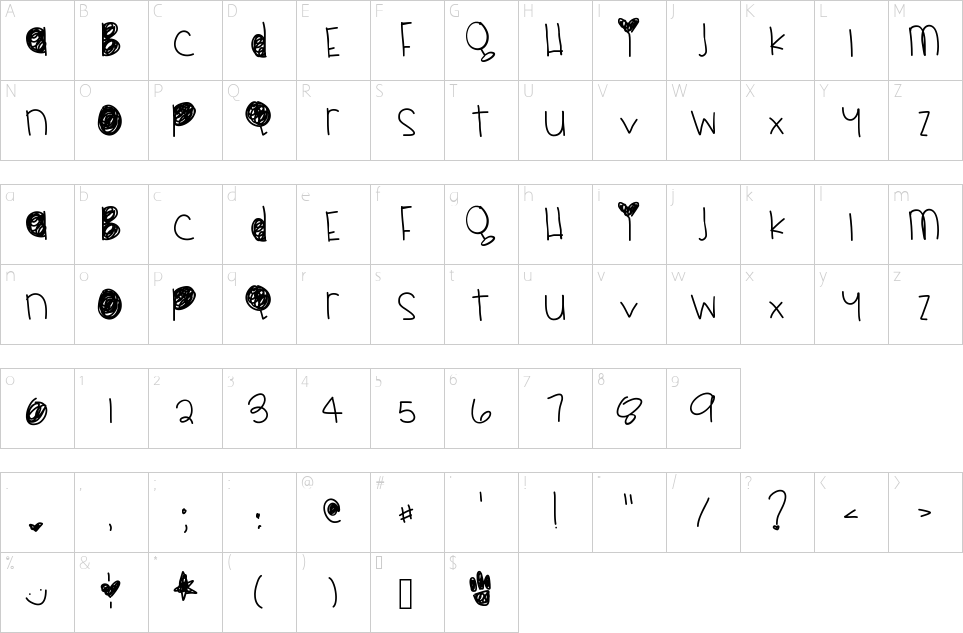
A fonte Pet Love é uma criação de Des Gomez, disponível gratuitamente tanto para Windows quanto para Mac. Com um design encantador e delicado, Pet Love é ideal para quem busca uma fonte que traga um toque especial aos seus projetos. Desenvolvida por uma mão atenta e criativa, esta fonte tem sido baixada cerca de 4.558 vezes, mostrando seu valor e agradando vários usuários que buscam um toque único em seus trabalhos. Seja para criar cartões de aniversário encantadores, adesivos personalizados ou até mesmo para adicionar um toque especial aos e-mails, Pet Love é uma escolha perfeita para os amantes de design e criatividade.